Nếu bạn vẫn nhầm lẫm giữa 2 khái niệm Typeface và font thì không nên bỏ qua bài viết dưới đây. Trong bài viết, ITPlus Academy sẽ làm rõ sự khác nhau của Typeface và font. Ngoài ra ITPLus cũng gợi ý cho bạn cách chọn phông chữ (font) thiết kế phù hợp nhé.
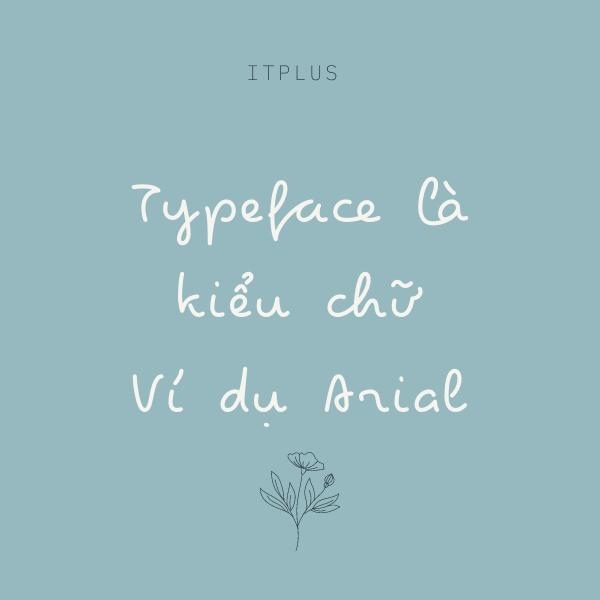
Typeface là các kiểu chữ. Có 5 nhóm typeface chính là Serif, San Serif, Script, Monoface, Fantasy Decoration.
Ví dụ Arial là typeface thuộc họ San Serif.
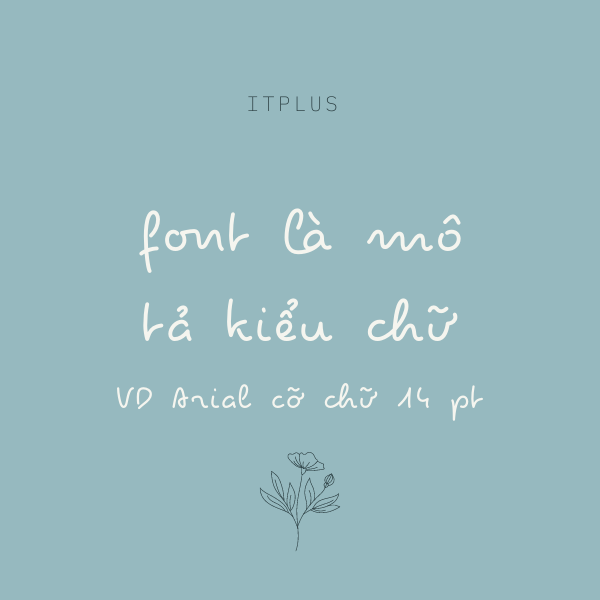
Font là mô tả đặc điểm cụ thể của typeface.
Ví dụ Arial cỡ chữ 20 pt là một font, Arial chữ in nghiêng là 1 font, Arial chữ in nghiêng cỡ chữ 20 pt là một font,...
Như vậy, Typeface và Font là 2 khái niệm khác nhau hoàn toàn. Typeface là kiểu chữ Arial nói chung còn Font Arial có đặc điểm cụ thể hơn về cỡ chữ,...
Mỗi font chữ đều có cá tính, màu sắc riêng vì vậy bạn cần cân nhắc việc font chữ nào sẽ phù hợp nhất với thiết kế của bạn nhé. Ví dụ font chữ có chân, đậm nét phù hợp với các thiết kế mạnh mẽ, vững chắc.
Ngoài ra, khi kết hợp các font chữ với nhau, designers có thể thay đổi kích cỡ, độ đậm nhạt, độ tương phản để đạt được hiệu quả thiết kế như mong muốn nhé.
Như vậy, bài viết đã giúp bạn phân biệt rõ ràng Typeface và font đồng thời gợi ý một số cách giúp bạn chọn được phông chữ thiết kế phù hợp. Chúc các bạn thành công!!!